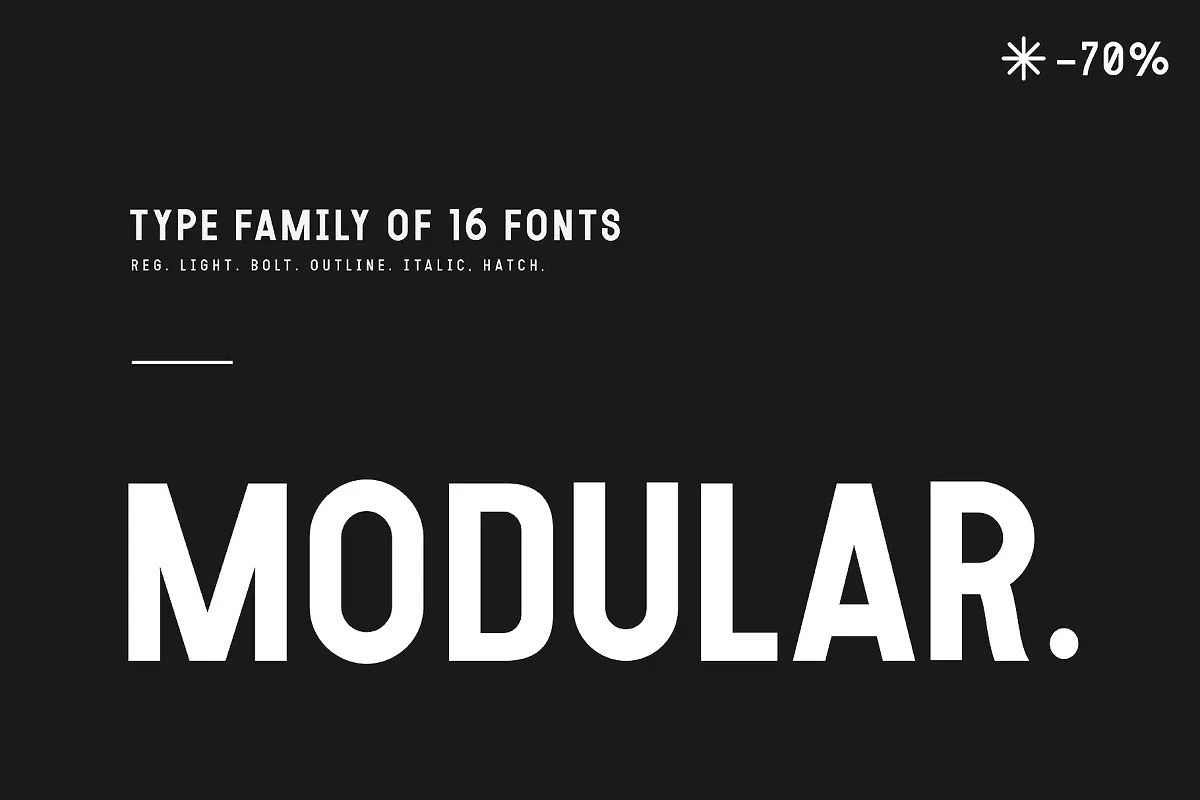
Introduzimos a Modular Typeface. Esta fonte permite que qualquer marca ou anúncio ganhe uma aparência fresca e futurista. Modular transmite a afinidade por tecnologia de maneira amigável, tornando-a fácil para os olhos. É uma tipografia em letras maiúsculas com um forte carácter, unificado e articulado. As curvas são levemente suaves, apresentando 16 pesos diferentes. Inspirada na precisão de terminais de computador, aplicações limpas e layout. A Modular proporciona uma composição de letra sincronizada, as letras maiúsculas se destacam excepcionalmente em experiências de interfaces da usuário, subtítulos, exibição independente e parágrafos curtos ou contéudos. Cada fonte no conjunto pode funcionar sozinha, apresentando dinâmica e autoridade. Elas são perfeitamente adequadas para serem usadas em exibições de 11. A Modular é uma ótima opção para criar uma identidade visual moderna e contemporânea. Para estabelecer a presença da sua marca de forma autêntica e imponente, recorrendo à modularidade desta fonte.